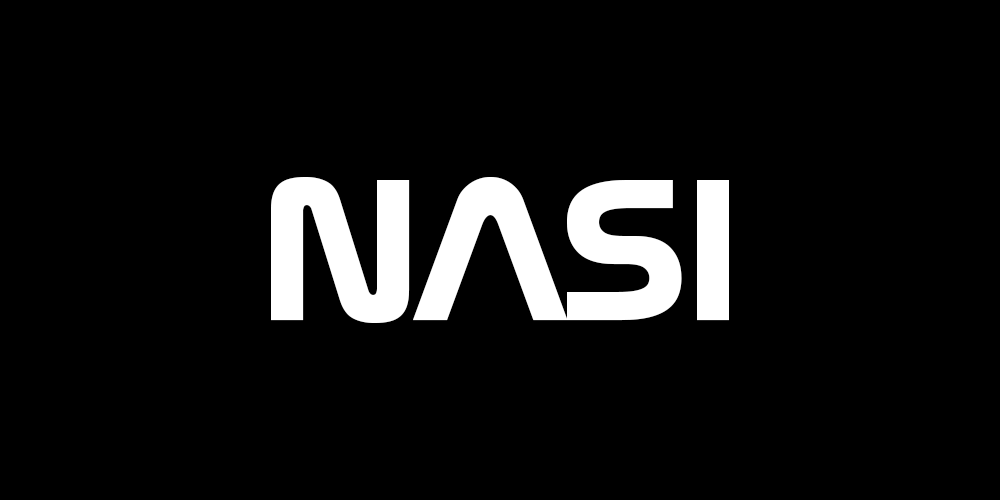
Font 1FTV Nasi
Bạn đang tìm kiếm một kiểu chữ độc đáo và ấn tượng cho dự án thiết kế của mình? Font 1FTV Nasi có thể là sự lựa chọn hoàn hảo dành cho bạn. Với thiết kế sáng tạo và hiện đại, mẫu font chữ không chân này không chỉ mang lại sự mới mẻ mà còn tạo điểm nhấn độc đáo cho bất kỳ sản phẩm nào từ tờ rơi, bìa sách cho đến các dự án đồ họa kỹ thuật số. Được ưa chuộng bởi các nhà thiết kế chuyên nghiệp, Font 1FTV Nasi hứa hẹn mang đến trải nghiệm thị giác thú vị, đồng thời thể hiện rõ nét phong cách và cá tính của bạn. Hãy khám phá sự khác biệt mà Font 1FTV Nasi có thể tạo ra cho các dự án sáng tạo của bạn ngay hôm nay!